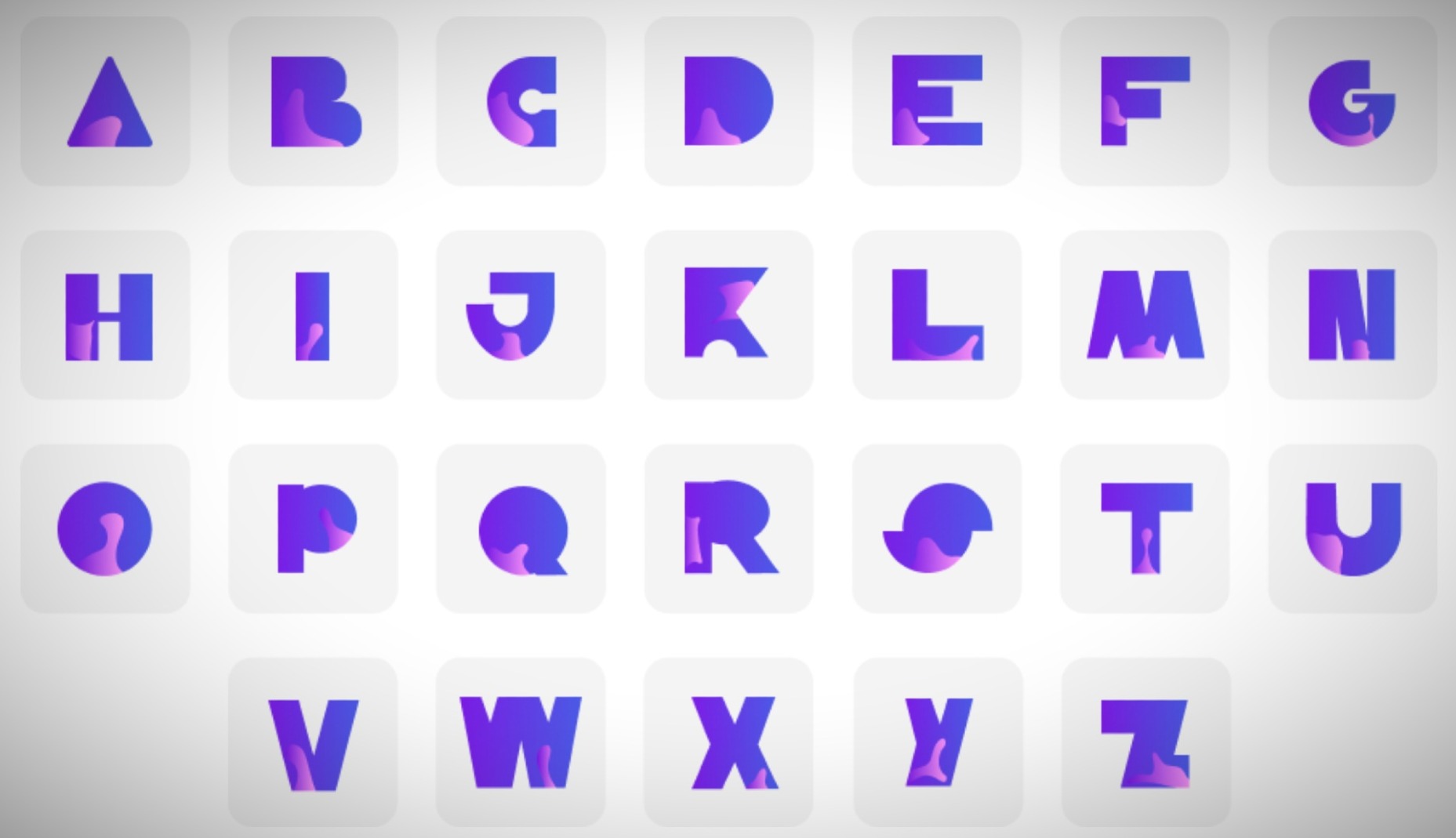
SmileType, una tipografía con fisuras para ayudar a los niños con labio leporino
• Ha sido creada por Proximity BBDO Colombia para promover donaciones a la fundación Fisulab
• La creación de las letras se ha inspirado en las fisuras de los niños afectados por esta condición
Uno de cada 800 niños que nacen en Colombia padece de labio leporino y/o paladar hendido, según datos de Fisulab, fundación dedicada a la rehabilitación de pacientes que sufren esta condición. Para conseguir fondos que ayuden a esta organización a realizar su labor, la agencia Proximity BBDO Colombia ha creado una tipografía inspirada en las fisuras de los niños con labio leporino que se presenta como elemento central de una campaña solidaria.
La creación de cada uno de los caracteres se ha inspirado en la fisura labial de un niño
Proximity BBDO Colombia ha elaborado un vídeo en el que presenta la tipografía y la campaña solidaria, al tiempo que se subrayan algunos datos sobre la realidad del labio fisurado y el paladar hendido; entre ellos, la posibilidad de que los niños que lo padecen sufran bullying y tengan problemas de comunicación y aprendizaje.
La pieza muestra asimismo imágenes de los niños en cuyas fisuras se han inspirado las letras y apela a la solidaridad para poder financiar sus operaciones, solucionar su problema y así completar las letras.